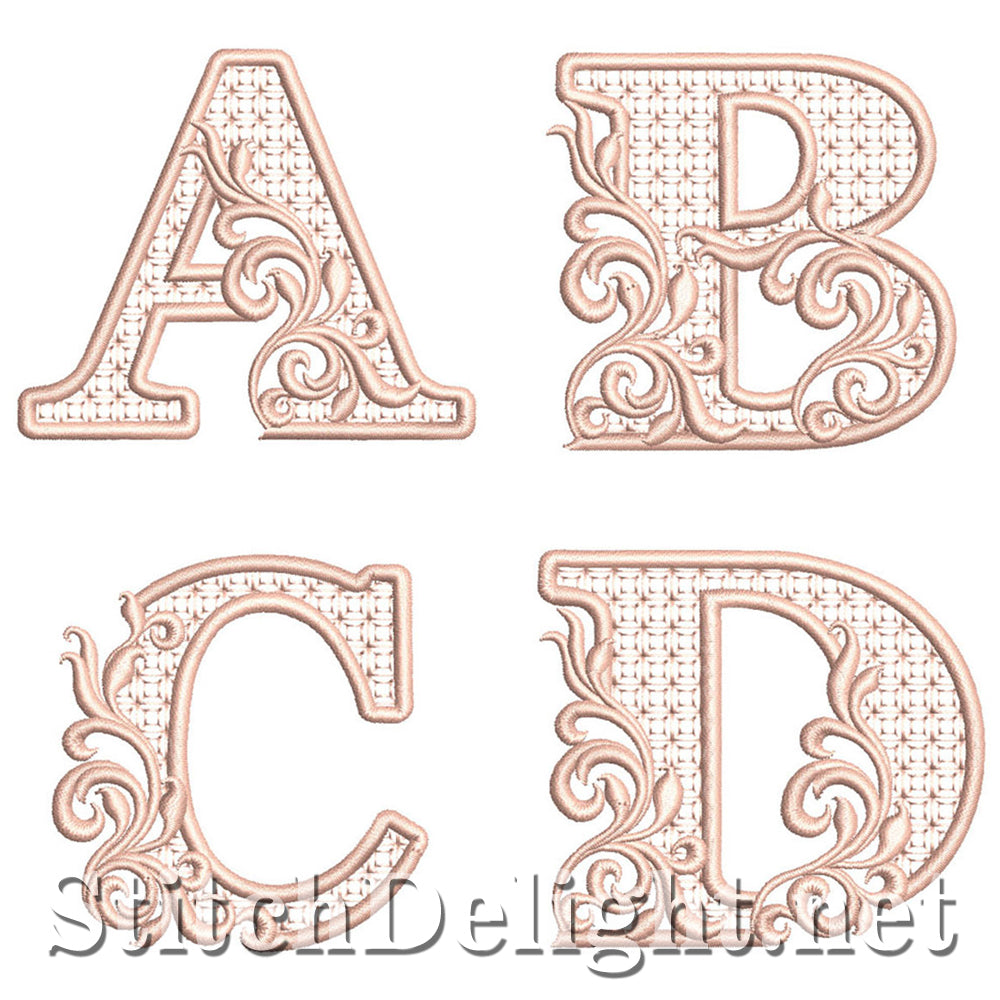
Belle police de bloc pour le cerceau 4x4 - avec des parchemins fantaisie - La hauteur des lettres est de 2,77" - Comprend MAINTENANT le format BX pour Embrilliance Essentials